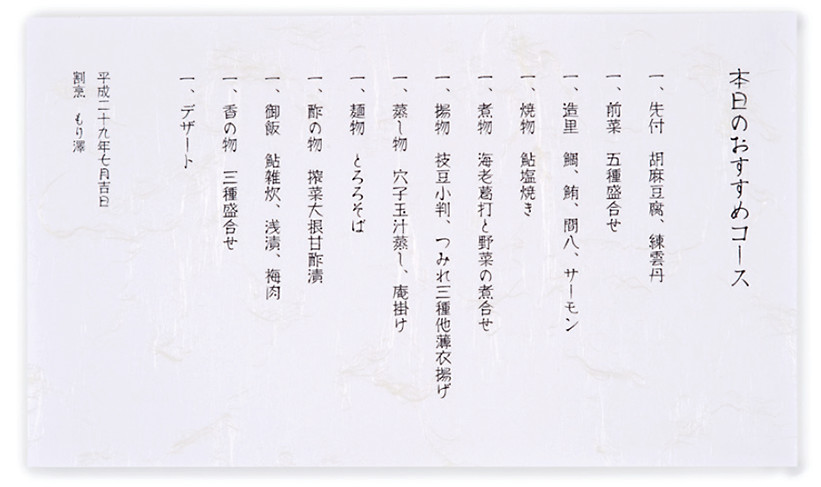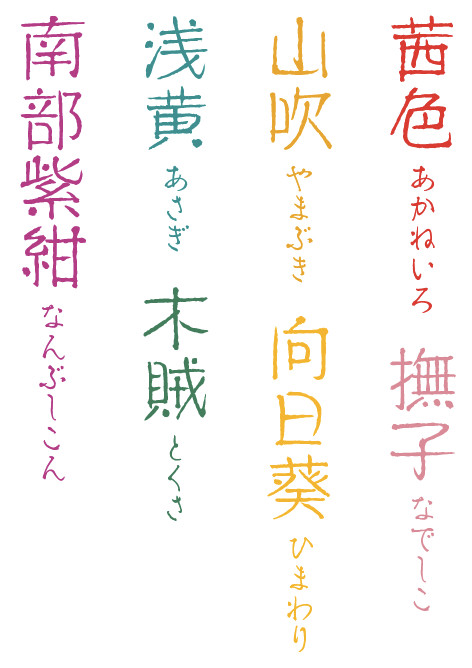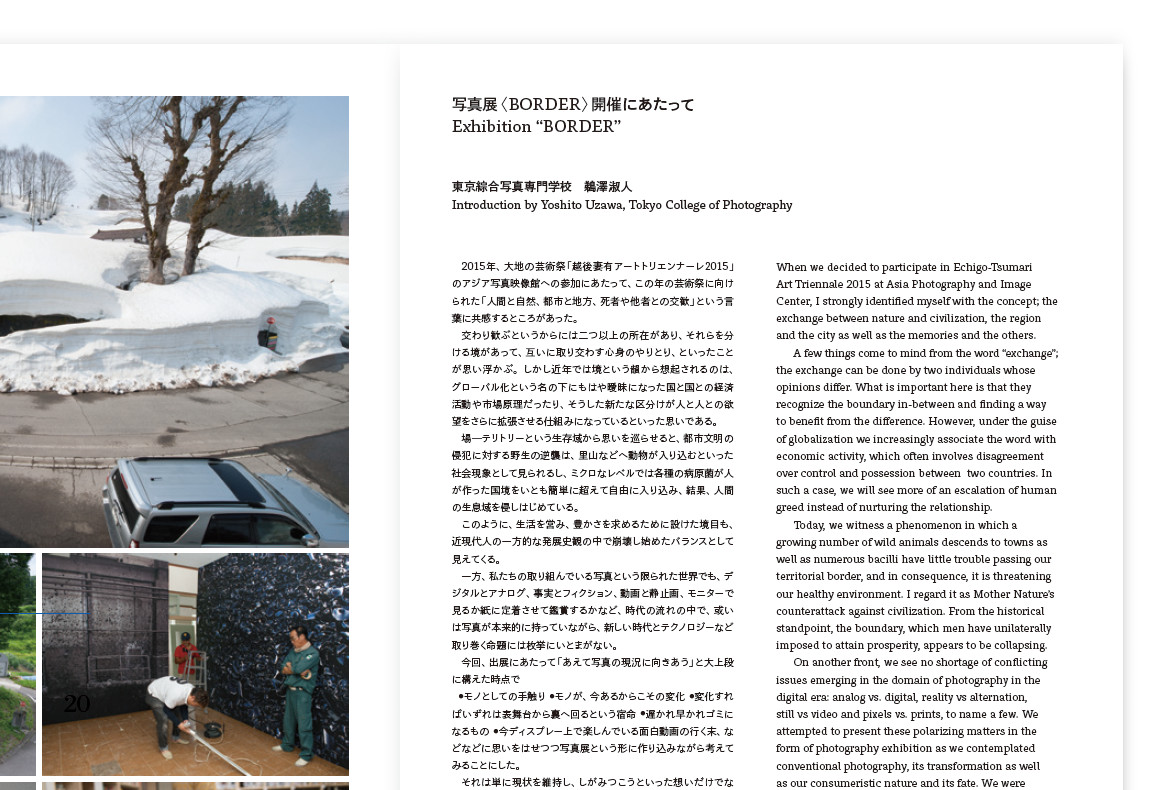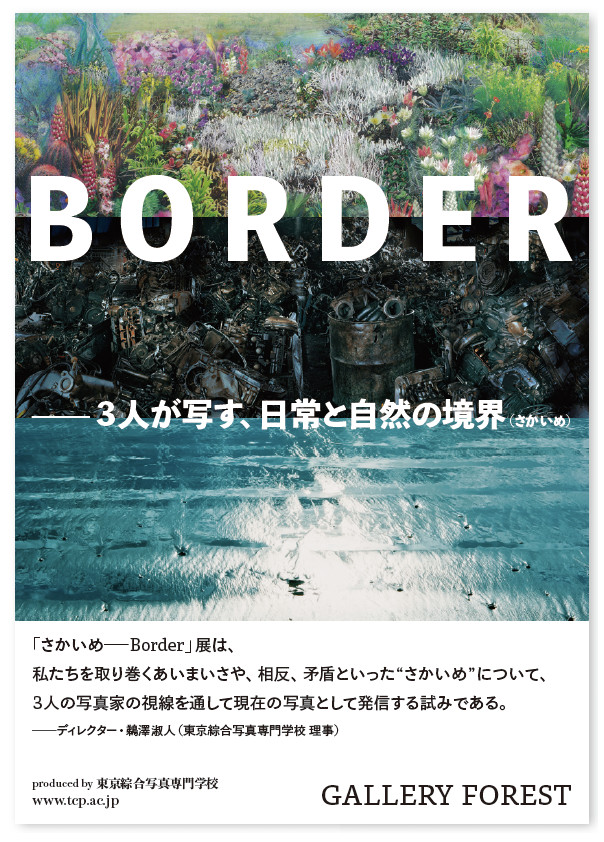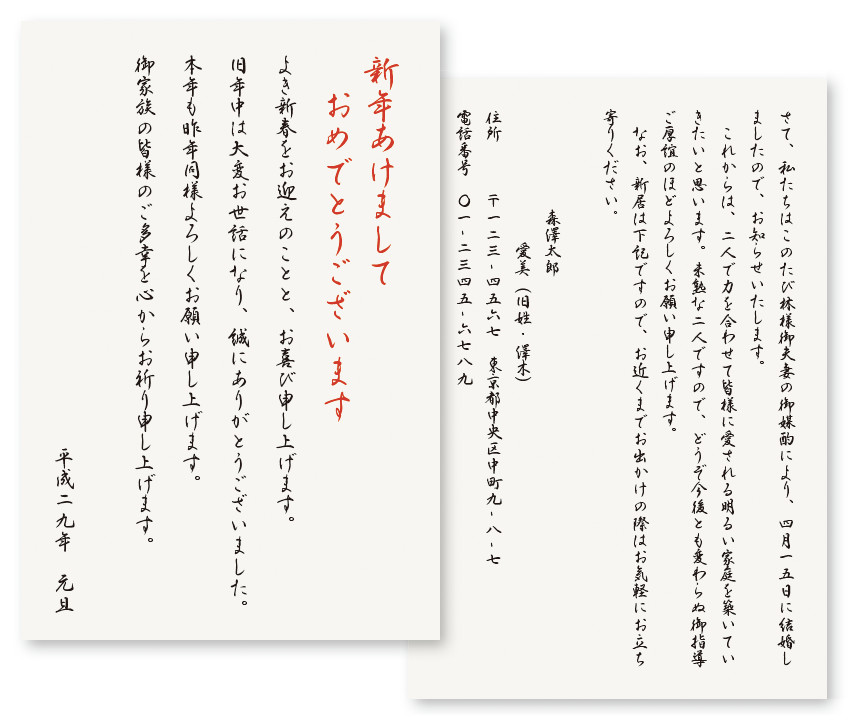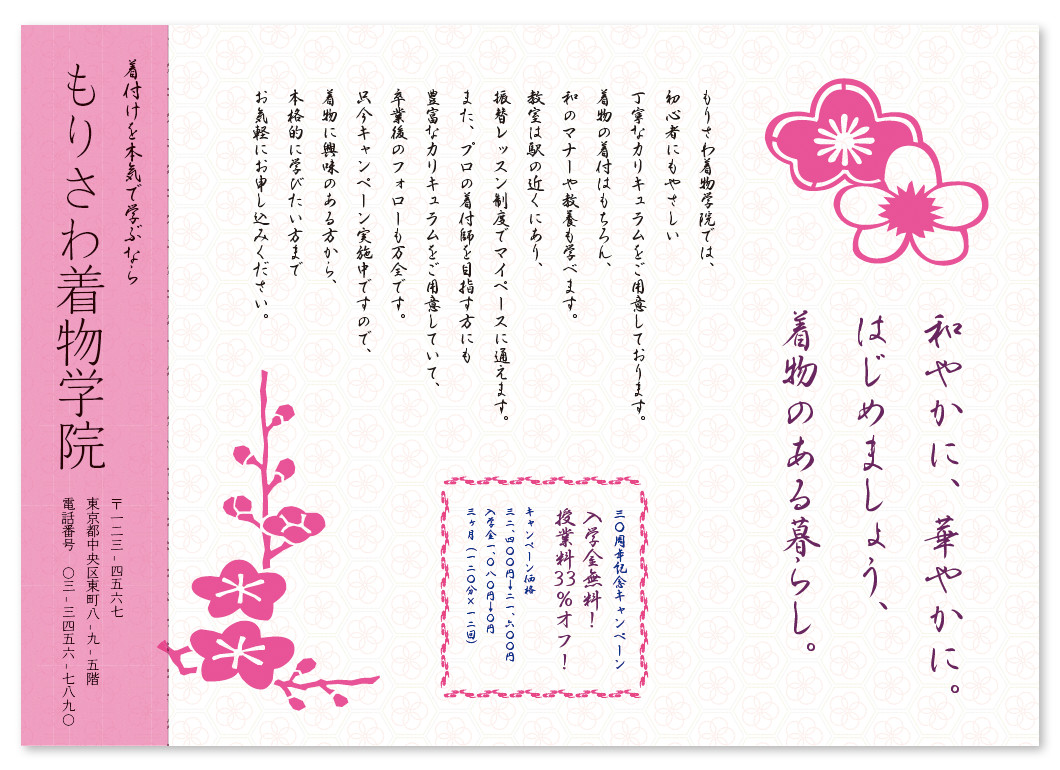
2016 モリサワ新書体
錦麗行書
「錦麗行書」は「タイプデザインコンペティション 2014」和文部門で明石賞に入賞し、製品化された書体です。(入賞時書体名:北原行書)この書体の特徴は、書家による筆文字の毛筆の雰囲気が残っている点にあります。文字は、手書きのバランスを残したまま、のびのびとデザインされており、画線にはにじみやかすれ、運筆の跡といった手の動きが見られます。どのような文字の並びであっても不自然にならないよう、丁寧に各文字が調整されており、組む文章が手書きのように見えます。挨拶状や宛名、のし紙といった手書きの筆文字が使われるシチュエーションや、筆文字の風合いを取り入れたい和のデザインなどで活用できます。
錦麗行書
錦麗行書、明石
凸版文久ゴシック DB
「凸版文久ゴシック DB」は、「凸版文久ゴシック R」にウエイトを追加する形でリリースされた、小見出しや本文に使えるゴシック体です。基本的な骨格は、凸版文久ゴシック Rを踏襲しており、デジタルデバイスでも読みやすい、横組みに特化された文字のデザインという、凸版文久ゴシックの特長を引き継ぎながらも、より視認性の高い、太めの本文・小見出し用ゴシック体として使えるように設計されました。凸版文久体ファミリーの全5書体が揃ったことによって、より統一感のあるデザインを作り上げることができるようになりました。
凸版文久ゴシック R /DB
凸版文久見出しゴシック EB
「凸版文久見出しゴシック」は、「凸版文久体」ファミリー全5書体のうち、見出し用のゴシック体にあたる書体です。「凸版文久見出し明朝」と同じように、凸版印刷オリジナル書体とその源流にあたる築地体を参考に作り上げたどっしりとした骨格に、角を落としたやわらかい肉付けをすることで現代的なニュアンスを加えています。シャープなエッジとモダンなデザインを備える英数字と相まって、クラシカルになりすぎない絶妙なバランスに仕上がっています。見出し書体にふさわしい力強さをもちながらも、どこか温かみを感じさせる書体なので、タイトルや見出し等、多くの場面で活用することができます。
タイトル・コピー:凸版文久見出しゴシック EB/
リード・右下:凸版文久ゴシック DB/左下:凸版文久見出し明朝 EB
秀英アンチック
「秀英アンチック」は、大日本印刷オリジナルのアンチック体を復刻した書体です。アンチック体とは、マンガのセリフや辞書の見出し、絵本などに使われる太いかな書体のことです。ゴシック体と並べても違和感がないよう、画線に太みの差をつけないようにデザインされており、手の動きを感じさせる重厚感のある文字が、仮想ボディいっぱいに書かれています。生命力あふれるその文字は、これまでセリフ表現や見出しとしての力強さが足りないと思えるようなシチュエーションにおいても、まるで肉声で話しているかのような、感情のこもったコミュニケーションに変えてくれる強さを持っています。「秀英角ゴシック金・銀 B」の漢字と組合せて使用することを推奨しています。
秀英アンチック
秀英四号かな
「秀英四号かな」は、金属活字の秀英四号明朝を復刻したかな書体です。「秀英3号」、「秀英5号」に比べて落ち着きのある、端正なデザインが特徴で、その骨格は現在デジタル化されている「秀英明朝」にも引き継がれています。「秀英四号かな」は、画線の先端に活版印刷のにじみのような適度な丸みを持たせており、筆の流れや手の動きを強く感じさせます。こうした処理により、「秀英四号かな」は「秀英明朝」よりもクラシックな印象に仕上がっています。書籍の本文のような読ませる文字だけでなく、タイトル・見出しなどにも活用することができるでしょう。漢字に「秀英明朝 M」を組合せることを推奨しています。
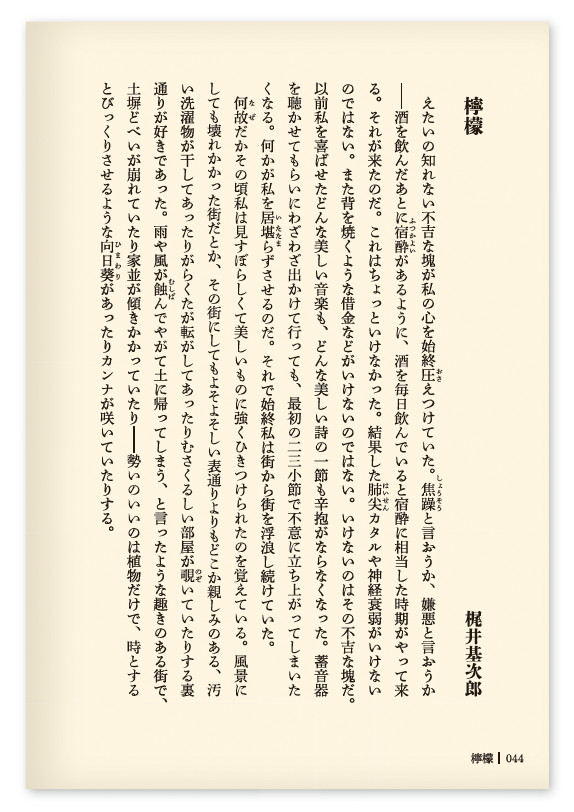
漢字:秀英明朝 M
かな:秀英四号かな ルビ:秀英明朝 M
秀英四号太かな
「秀英四号太かな」は、見出しや児童書の本文に使われていた秀英体の金属活字・秀英四号明朝太かなを復刻したかな書体です。太い筆で力強く書かれたような文字は、筆勢を活かしながらも画線が整理されている「秀英初号明朝」と比べると、より筆の運びが生む画線のうねりがしっかりと残っています。「秀英初号明朝」の漢字と同程度の黒みになるよう、調整が施されており、「秀英初号明朝」の漢字と組合せて使うことで、「秀英四号太かな」の表現力をもっとも効果的に引き出すことができます。
秀英四号太かな
うたよみ
「うたよみ」は、書家による毛筆の文字をもとに作られた筆文字系デザイン書体です。文字の大きさや画線の太さ、仮想ボディ内でのバランス、線のかすれなどをあえて整えすぎないように設計されており、手書きならではのぬくもりを感じさせます。個々の文字は組んだ時にバランスよく見えるよう、重心が細かく調整されており、特に縦組みの際に最適な文字組みになるようにデザインされています。緩やかなカーブを描く縦画に対して、隷書の波磔のような勢いのある横画、繊細な左払いに対して、ダイナミックな右払いなど、静動入り混じる独特な書風となっています。品性と大胆さを兼ね備えた独創性があり、パッケージや広告、和食のメニューなど、格調を求められる場面で効果を発揮する書体と言えるでしょう。
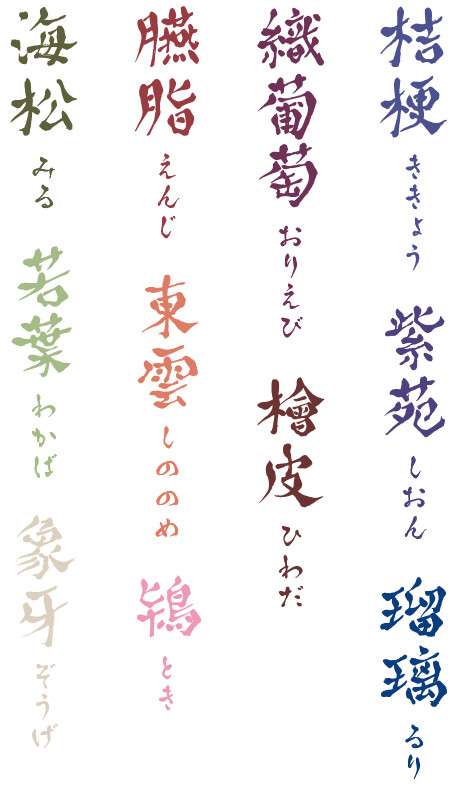
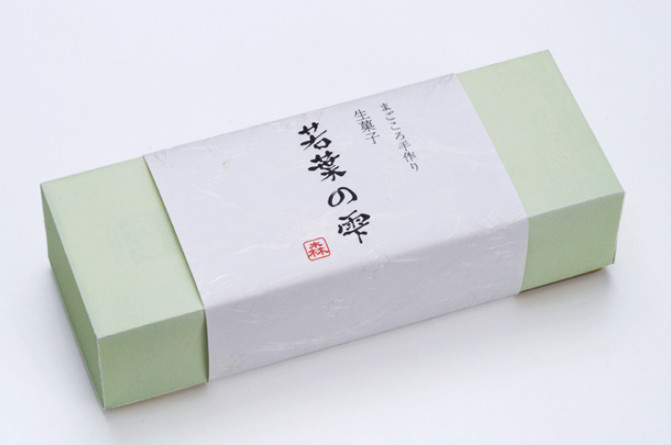
うたよみ、徐明
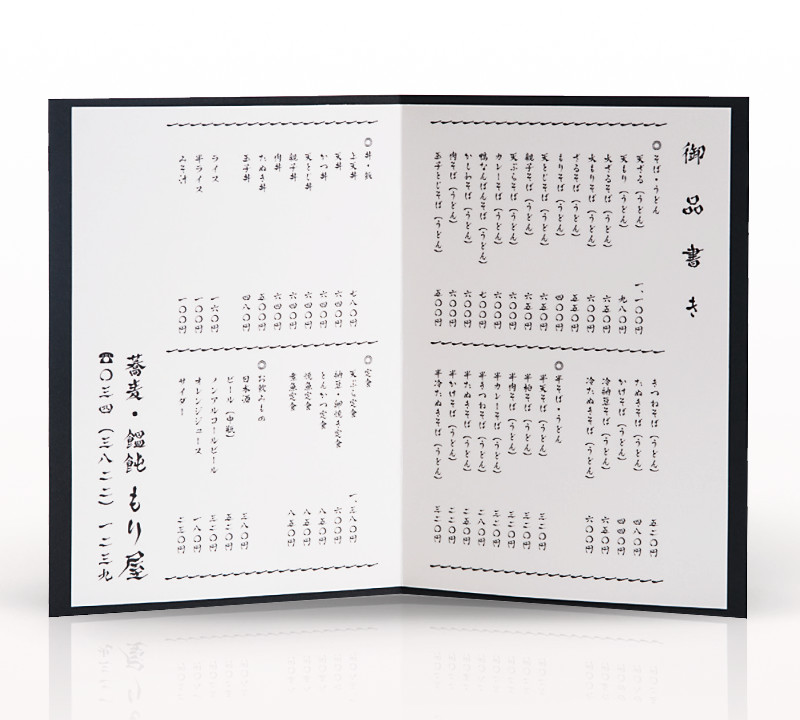
はせ筆
「はせ筆」は、筆ペンの風合いを残す、しなやかでやわらかい骨格を備えたデザイン書体です。肉筆ならではのにじみのある線や、画線のはみ出し、角や点に残るインクのたまりが、文字にあたたかみのある表情を与えています。漢字は正方形を意識した、しっかりとした骨格ですが、独特の画線処理によって可愛いらしい、ポップな印象も感じさせます。ひらがなは重心を低く設定した、落ち着きのある上品なデザインで文章も組める、高い可読性を備えています。英数字は、インクのたまりがアクセントとなっており、和文と合わせても違和感のないデザインです。ポスターや広告のキャッチコピーやパッケージのように、大きなサイズで見せる文字としても、メニューや挨拶状などで読ませる文字としても使いやすさがあります。縦組みでも横組みでも調和のとれた文字組みが可能なオールマィティな書体です。
昭和書体
昭和書体の毛筆フォントは、リアルな直筆に近い趣を備えていることが特徴です。昭和書体は、さまざまなタイプの筆文字をフォント化しており、毛筆書体のなかに多種多様なバリエーションを生み出しています。画線には、毛筆の特徴であるかすれが大胆に残り、デジタルフォントでありながら、直筆と思えるようなリアリティを備え、「目に、意識に留まる文字」をコンセプトに大胆にデザインされた書体群は、組まれた文字そのものの形が受け手に強いイメージを伝えるパワーを持っています。2016年の新書体として、楷書体の「昭和楷書」、デザイン書体の「闘龍」「黒龍」「銀龍」「陽炎」の計5書体が追加されました。経験と歴史に裏打ちされた和文毛筆フォントを、ぜひご活用ください。
闘龍、銀龍
昭和楷書
タイ文字
アップグレード2016では、お客様から要望の高かった多言語フォント「タイ文字」が提供されます。タイ文字といえば、文字にループがあることで、書かれている言語がタイ語であるとわかるケースも多いですが、すべてのタイ文字にループがあるわけではありません。フォントによってはループを閉じないものや、塗りつぶしているもの、ループがまったくないものもあります。幅広い用途でお使いいただけるよう、伝統的なデザインからモダンなデザインまで、タイ文字60書体がライナップされました。これらのタイ文字のフォントベンダー、DB Designs(42書体)、Cadson Demak(12書体)、Katatrad Aksorn(6書体)の3社を紹介します。
DB Designsについて
企業向けのグラフィックデザインを手がける「Dear Book Co., Ltd」として設⽴され、1987年にデジタルフォントを制作したことを契機に、書体デザインを本格的に開始。1999年「DB Designs」に社名変更し、2006年よりDBブランドのフォント制作と販売をしています。
Cadson Demakについて
2002年、Anuthin Wongsunkakonにより設⽴されたバンコクのタイプファウンダリです。タイポグラフィーとデザインに対する愛情と、フォント産業全体の発展と現代化、そして書体の日常的利用をより浸透させるという理念を持っています。
Katatrad Aksornについて
2011年設立。タイ中部のチョンブリーを拠点に、才能と書体デザインへの愛にあふれる、現地の若手2名によって運営されています。タイでは唯一となる、バンコク以外で法人化されているタイプファウンダリです。